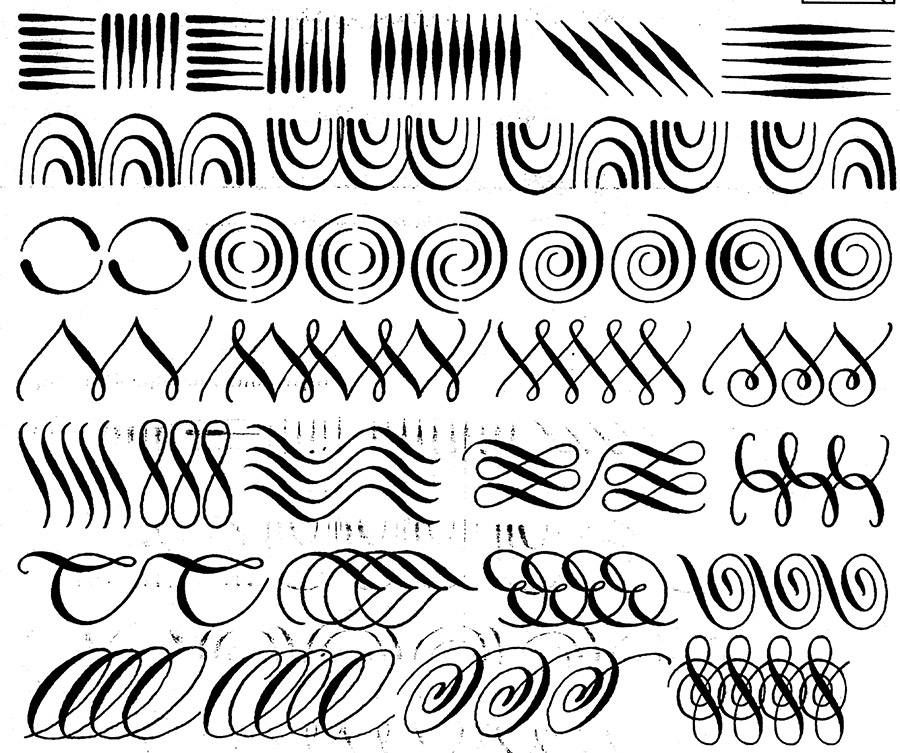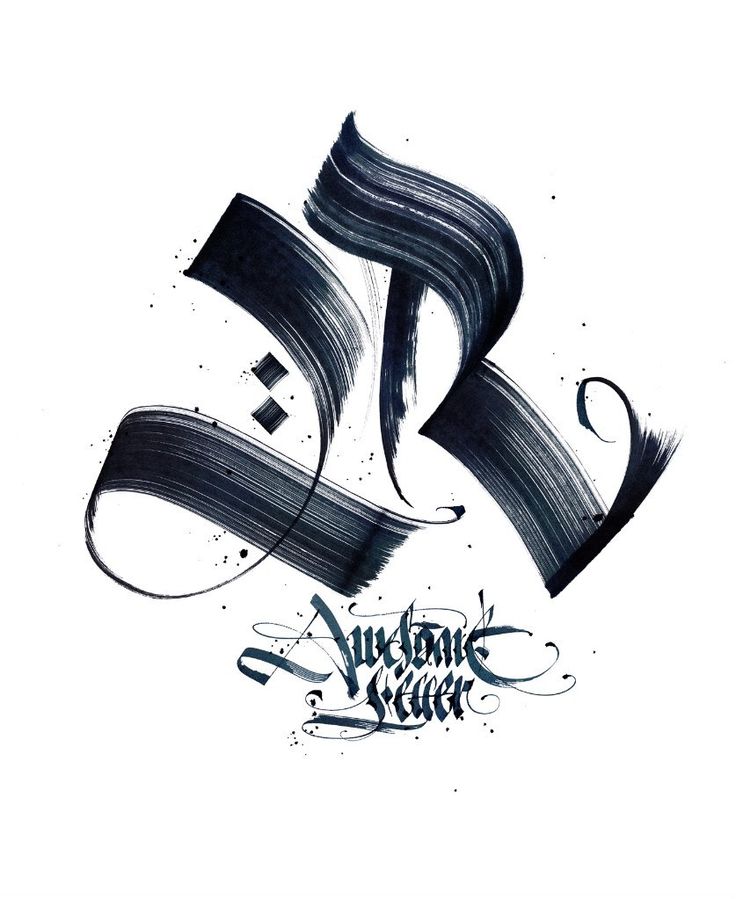
таких однородных букв на разных конструктивных началах нарушает
весь стиль шрифта независимо от того, по какому принципу скон¬
струированы все остальные буквы с округлыми элементами.
Как известно, уже в эпоху Возрождения создавалось много трак¬
татов по конструированию шрифтов разных рисунков и стилей. Осо¬
бое внимание по праву обращалось на шрифты типа антиквы. В дан¬
ной книге приведены некоторые образцы конструирования букв
великими мастерами прошлого. В дополнение к ним дается несколько
других примеров, исполненных с учетом как опыта мастеров прош¬
лого, так и практических требований современности.
abcdefßhijk Im
abcdef&h ijkt
Два принципа исполнения шрифта — два типа инструментов. Вверху — шрифт,
написанный ширококонечным пером, внизу — рисованный шрифт.
В соответствии с этим расположены и орудия выполнения:
1 — гусиное или тростниковое перо; 2 — металлическое ширококонечное перо;
3 — ширококонечное перо для выполнения крупного шрифта; 4 — плоская
кисть; 5 — перо из дерева; 6 — тонкое перо; 7 — остроконечная кисть;
S — игла; 9 — штихель
Наиболее распространенный способ конструирования шрифта —
построение букв в квадрате.
Для примера составим конструкцию ан¬
тиквы. Прежде всего установим, какую часть стороны квадрата зай¬
мет основной штрих, т. е. определим светлоту шрифта. За толщину
основного штриха примем Vio стороны квадрата. Это будет единицей
измерения основного штриха для всех букв алфавита. Затем разде¬
лим все стороны квадрата на 10 равных частей и вычертим сетку. Она
поможет конструировать буквы и следить за расположением отдель¬
ных элементов. Толщина соединительных штрихов составляет опре¬
деленную часть толщины основного штриха, например, Ч->, ‘/з и т. д.
В настоящей книге помещено несколько алфавитов рубленого
(гротескового) шрифта, сконструированных при помощи сетки (стр.
принципам, но сетка не показана (стр. 144—145). Здесь в компоновке
букв важную роль играют круги разного диаметра (Vio, 2/ю или 3/ю
стороны квадрата). С помощью тех же кругов образуются и засечки.
Шрифт можно построить и на основе различных прямоугольни¬
ков, ромбов и других фигур; в зависимости от этого получим буквы
узкие или широкие, прямые или наклонные.
Во всех этих случаях
правила те же, что и при построении шрифта на основе квадрата.
В иллюстрациях к данной главе приведены буквы с Траяновой
колонны, взятые из книги Л. С. Иветса «Римские буквы» («Roman
Lettering»). Алфавит из этих знаков дополнен несколькими буквами
более позднего происхождения. Буквы римской антиквы, ставшие
классическим образцом, исследовались в оригиналах и анализирова¬
Верхняя строка — схема исполнения букв плоской кистью. Средняя строка —
те же буквы высечены на камне, причем предварительно приспособлены к этой
технике исполнения. Нижняя строка — те же буквы на пергамене. Некоторые
детали букв, написанных плоской кистью, отделаны остроконечной
Были и попытки выработать основы конструирования строчных букв
антиквы, но так как в строчных буквах разных элементов больше,
чем в прописных, то и законы конструирования были очень сложными.
Поэтому строчные буквы, а также курсивные, орнаментированные и
все другие буквы сложного начертания строятся от руки на глаз на
основании классических пропорций и строгой ритмичности.
В образцах шрифтов, о которых говорилось выше, остроконечные
линии квадрата. Это не является неточностью рисунка, — так устра¬
няется оптическая иллюзия, будто одни буквы строки ниже других.
Отправными формами при рисовании букв являются H и О. На
основании этих букв можно построить весь алфавит. Буква Н, напри¬
мер, определяет ширину и высоту букв, толщину основных и соеди¬
нительных штрихов, местоположение срединных штрихов и харак¬
тер засечек. Буква «О» определяет характер округлых форм и распо¬
ложение нажима (вертикальное или наклонное).